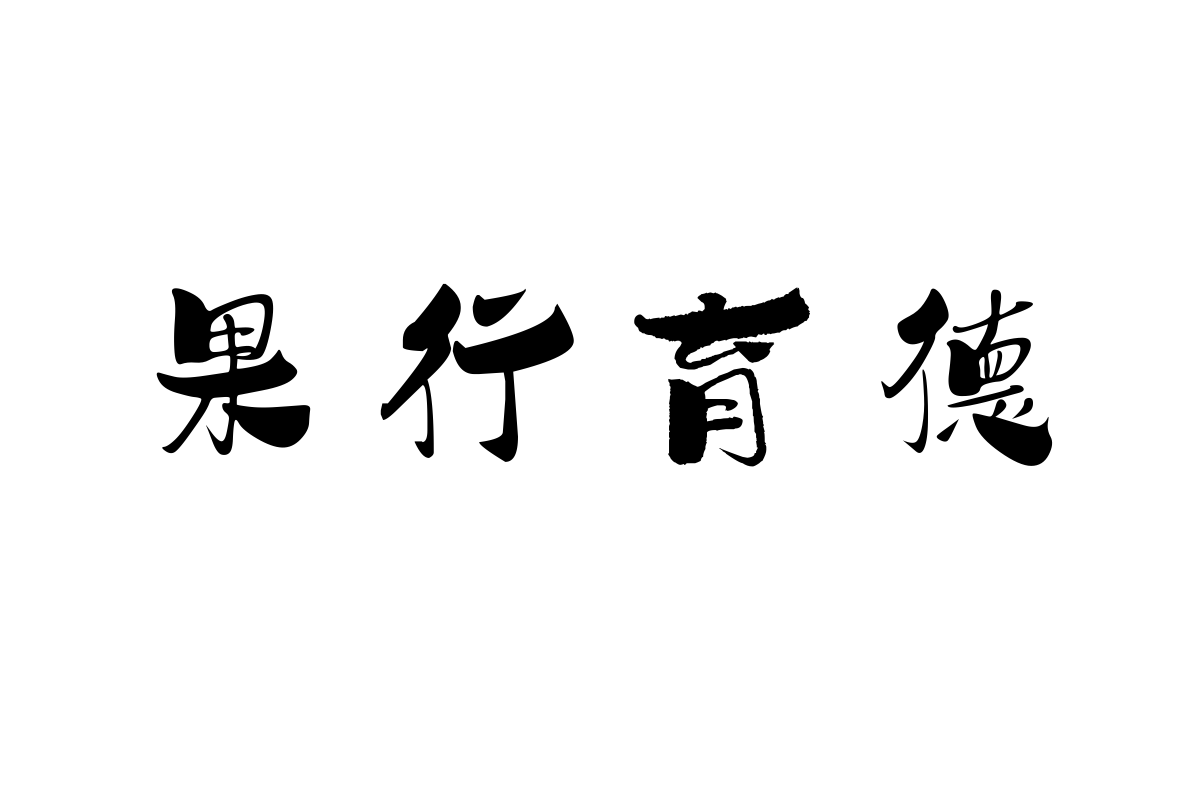
汉标学步体是一款具有独特风格和特色的字体。它采用了传统的书法元素,结合现代设计趋势,创造出一种既古典又时尚的字体。这款字体的特点包括:
1. 独特的笔画结构:汉标学步体的笔画流畅自然,线条优美,给人一种优雅而庄重的感觉。
2. 丰富的字形变化:这款字体包含了多种不同的字形,可以根据不同的设计需求进行调整,满足多样化的设计需求。
3. 良好的可读性:虽然汉标学步体在视觉上非常吸引人,但它仍然保持了良好的可读性,使得文本内容依然清晰易读。
4. 适用于多种场景:无论是广告、海报、包装还是网页设计,汉标学步体都能很好地融入其中,展现出其独特的魅力。
总的来说,汉标学步体是一款极具创意和个性的字体,适合用于需要展现独特风格的设计项目。